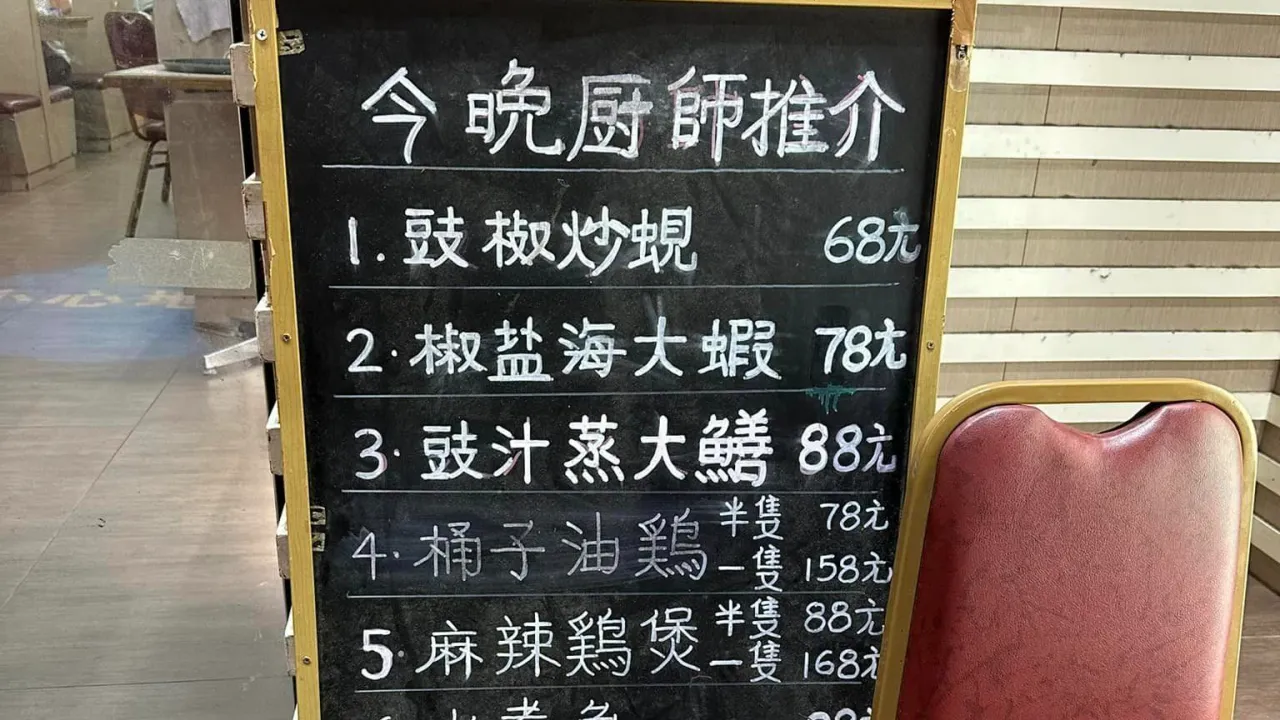
旺角酒樓黑板餐牌驚現神級粉筆字 手寫美觀如電腦字體 網民狂讚︰被飲食業耽誤的書法家
旺角隱藏著不少令人驚喜的特色小店,過往曾有網民在社交平台發文,分享在旺角通菜街一間酒樓發現極具特色的黑板餐牌,上面所有菜式均由員工以粉筆親手書寫,筆跡無比工整平實,隨即引發熱議。不少網民大讚這款極具誠意的手寫字體,更搞笑封撰寫者為「被飲食業耽誤的書法家」。除了字體吸睛之外,更有不少街坊及食客力薦該店的小菜經濟實惠,大讚「好嘢又抵食」!
過往曾有網民於Facebook群組「香港茶餐廳及美食關注組」發帖,分享於旺角發現一間餐廳餐牌上,全部菜式項目均以粉筆手寫,並形容「真心覺得佢手字好得」,成為餐廳引人注目的焦點。從相片中可見,當時餐牌上的手寫字相當整齊,不論中文字體抑或價錢細,同樣寫得不錯。
貼文當時引來大批網民留言,有人大讚字體平實功整,笑指寫得一手好字的店員(或廚師)是「被飲食業耽誤的書法家」、「飲食界欠他一個交待」,更加有網民表示「終於有人睇到」、「建議收納為新電腦字體」,連餐廳內的餐牌,同樣均以手寫,可見誠意十足。